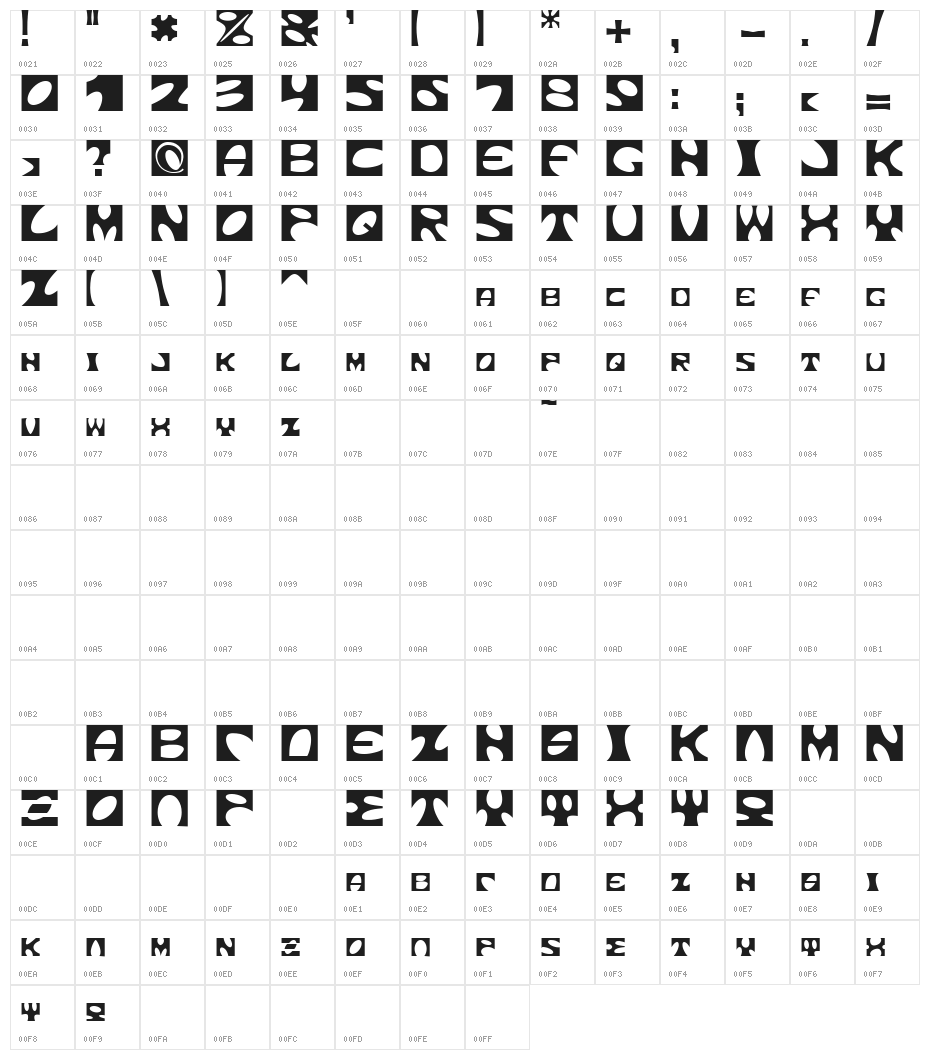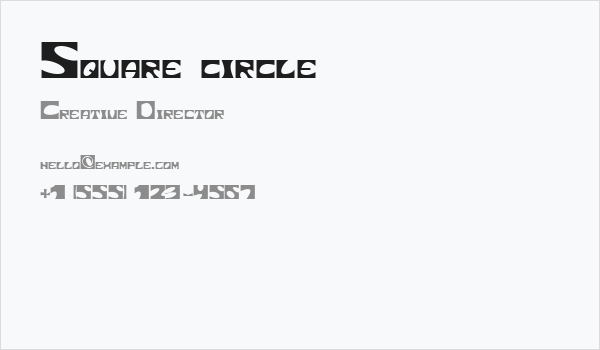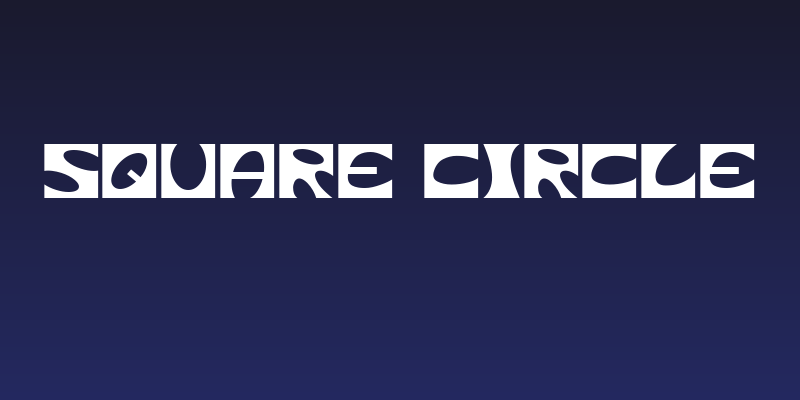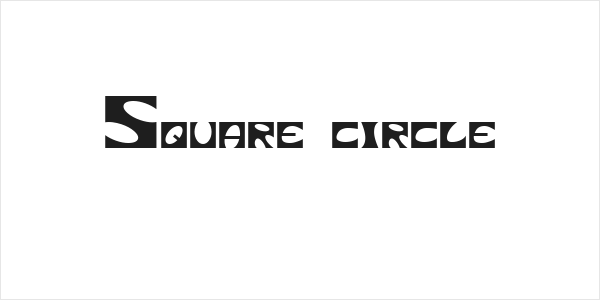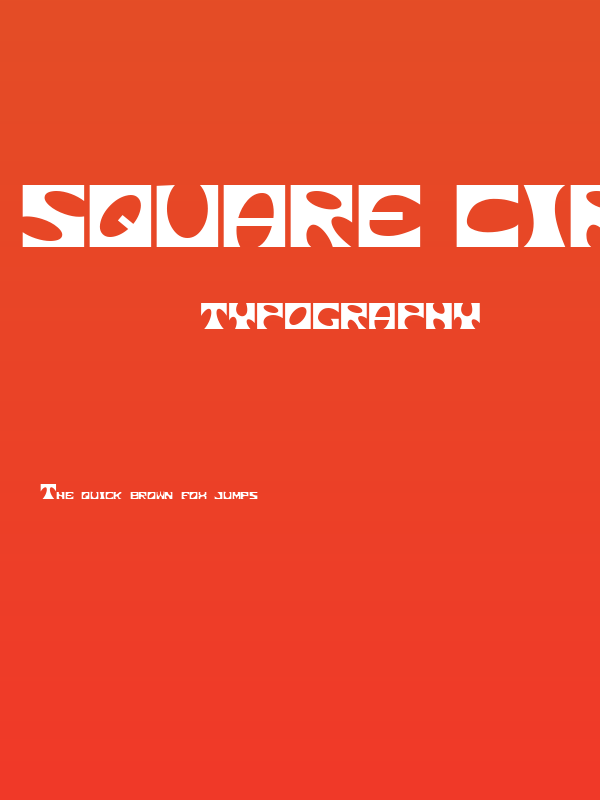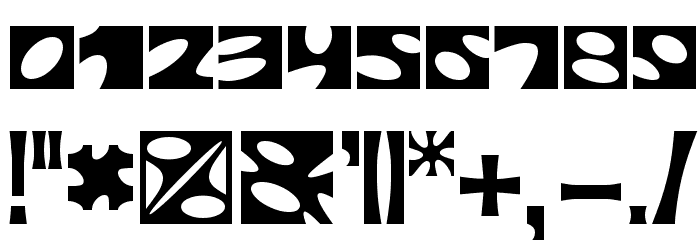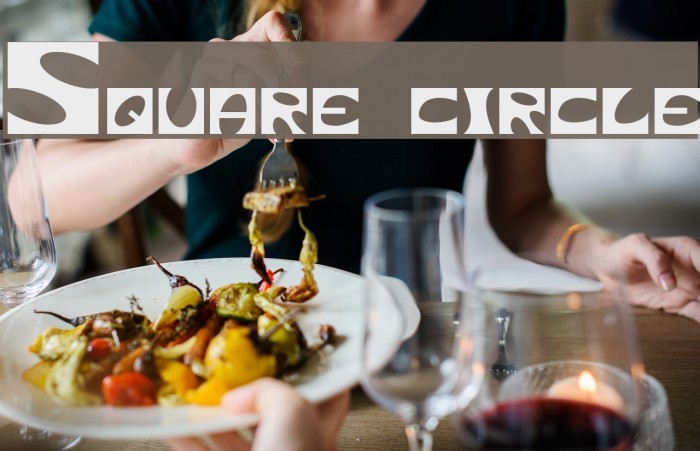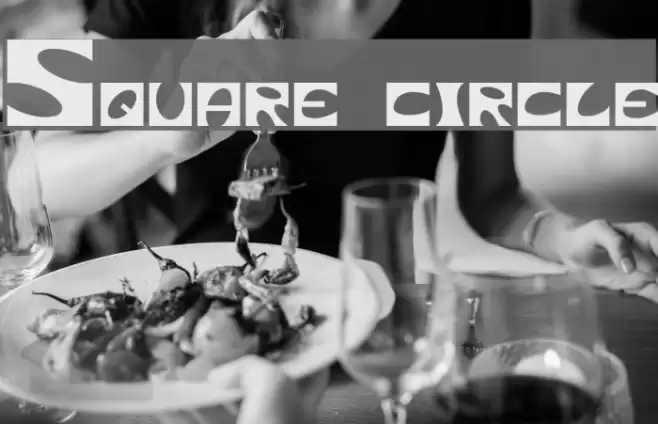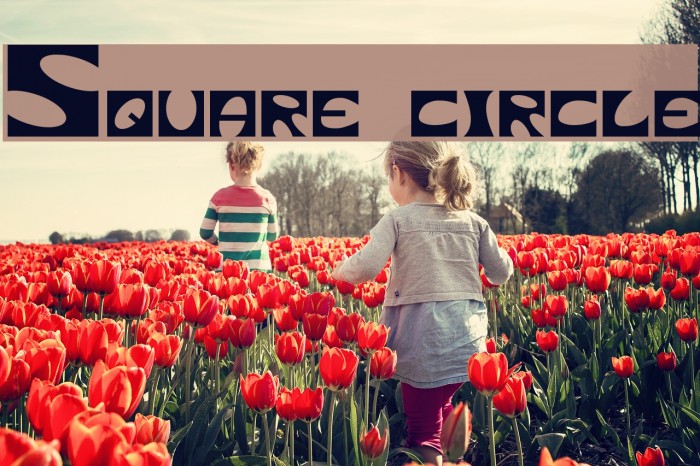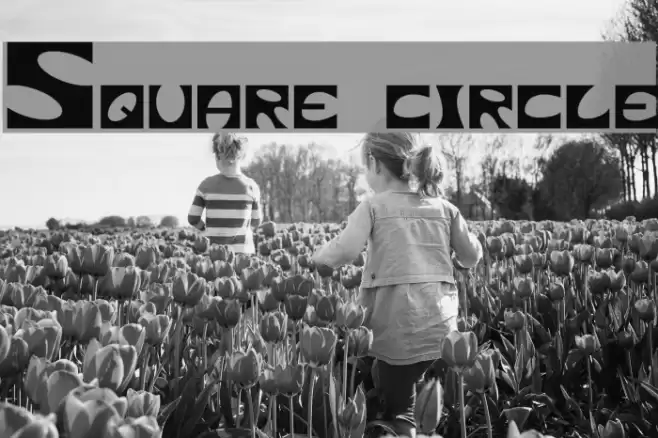
Square circle Font
| おすすめプロジェクト | This font is perfect for branding, posters, album covers, and any project that requires a modern, artistic flair. |